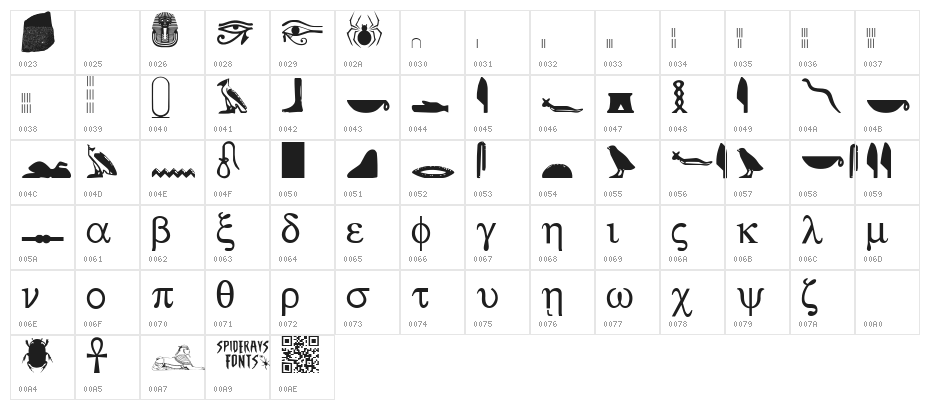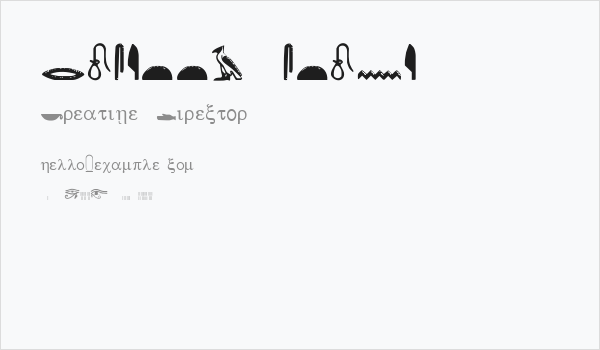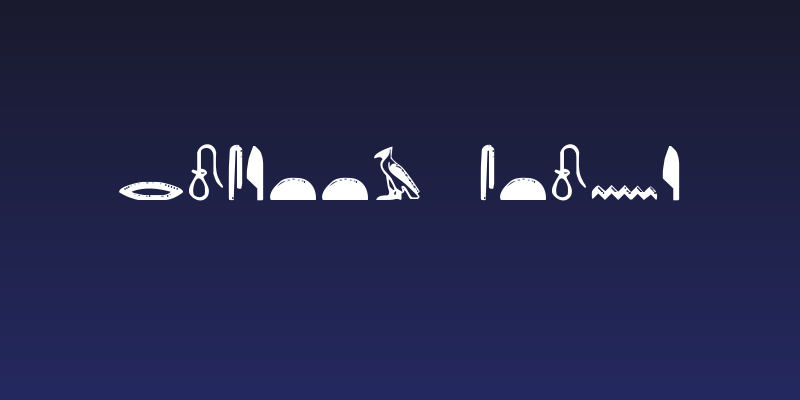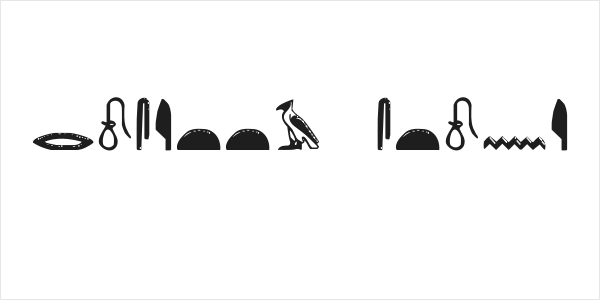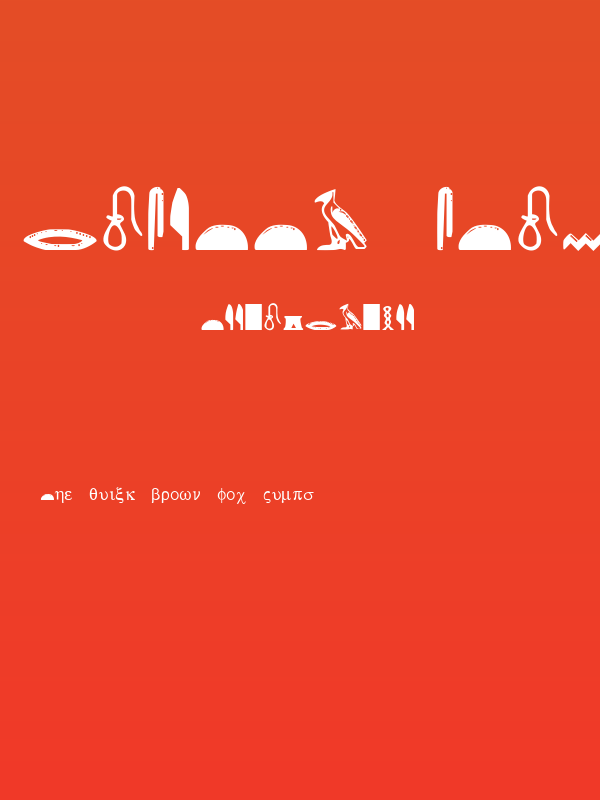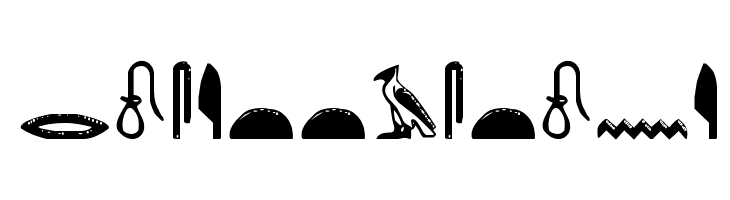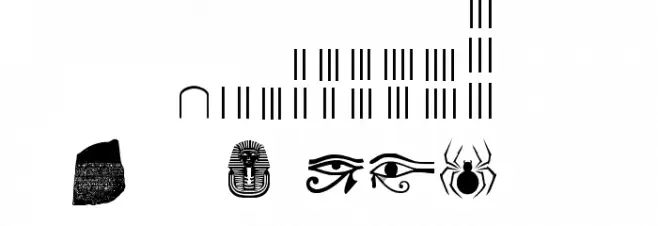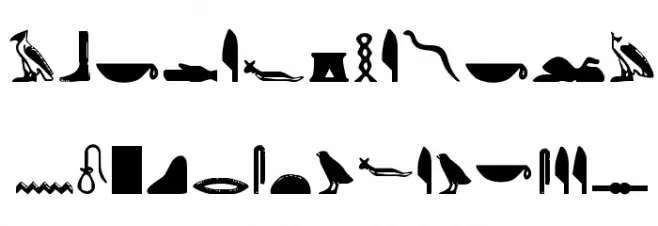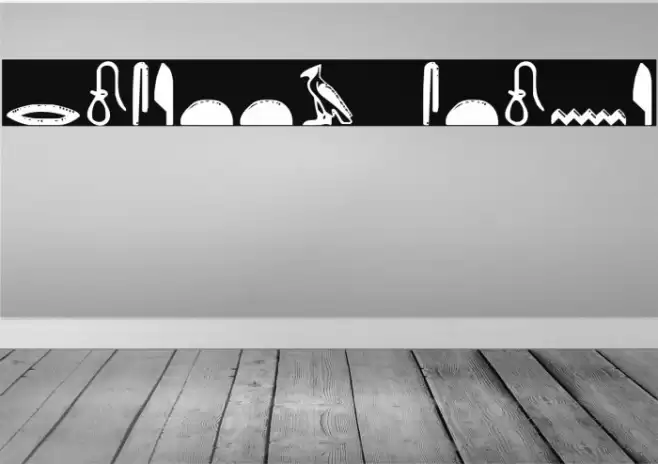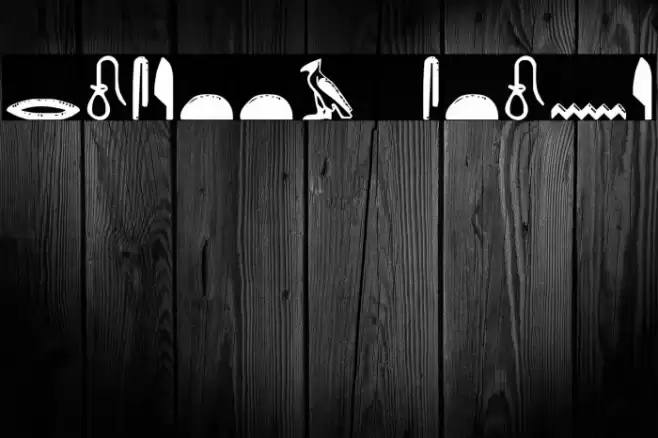
ROSETTA STONE Font
ROSETTA STONE
| Категория | Calligraphic |
| Общий стиль | Historical, Decorative |
| Область применения | Logos, Educational materials, Themed events |
| Рекомендуемые проекты | Ideal for educational materials, historical documentaries, themed events, and cultural exhibitions. |